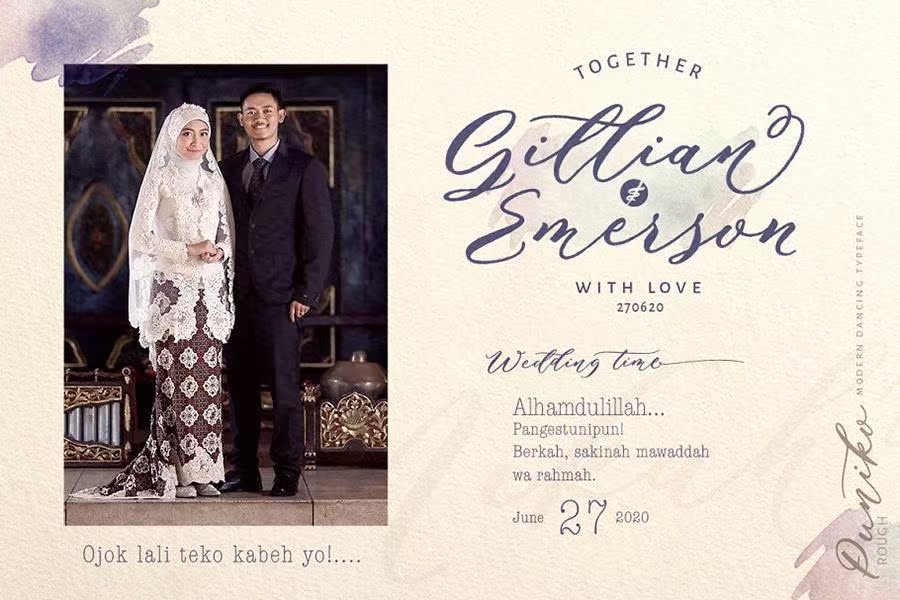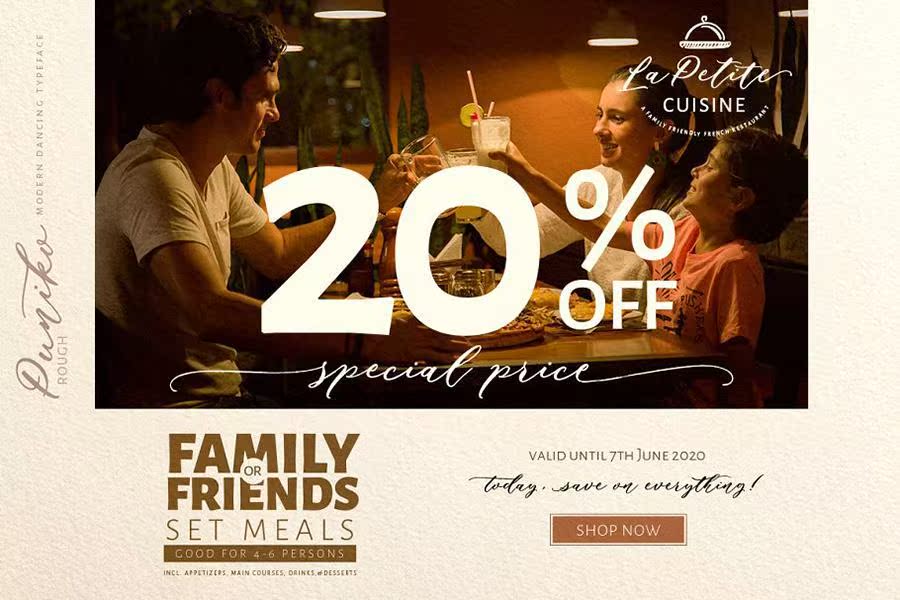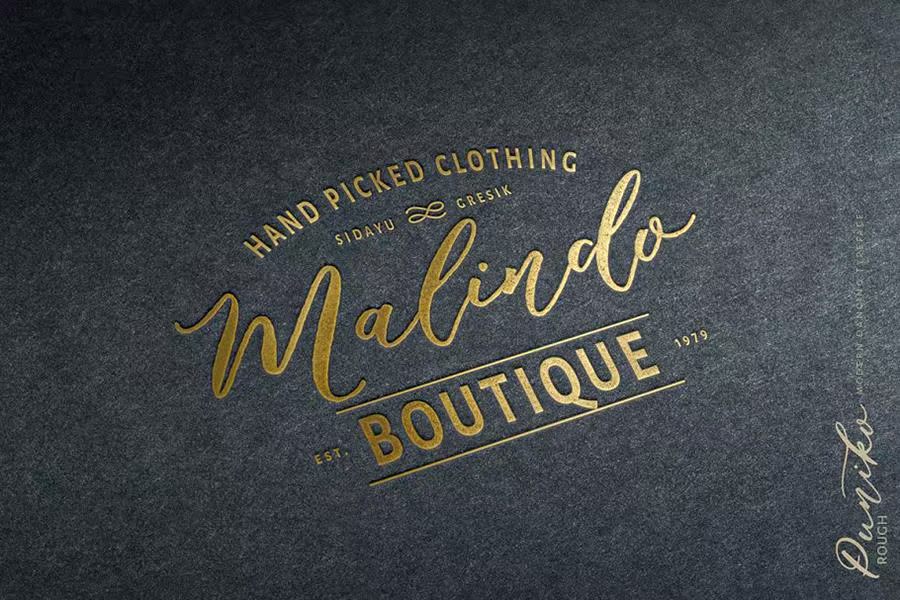
PUNIKOR通过脚本演示和字母流程来实现自然曲线的完美组合。如果要创建此字体,请使用一个不超过两个字符的字体,以便更好地使用所有类型的打印技术、刺绣、激光切割、金箔等。适用于婚礼、邀请、问候卡、报价、海报、品牌、名片、文具、设计标题、博客标题、艺术报价、,印刷艺术、现代发展趋势、书籍设计、绘画和设计或水彩设计主题、工艺设计、任何DIY项目、书名、婚礼字体、流行设计,或任何旨在使您的艺术/设计项目看起来漂亮和时尚的目的。